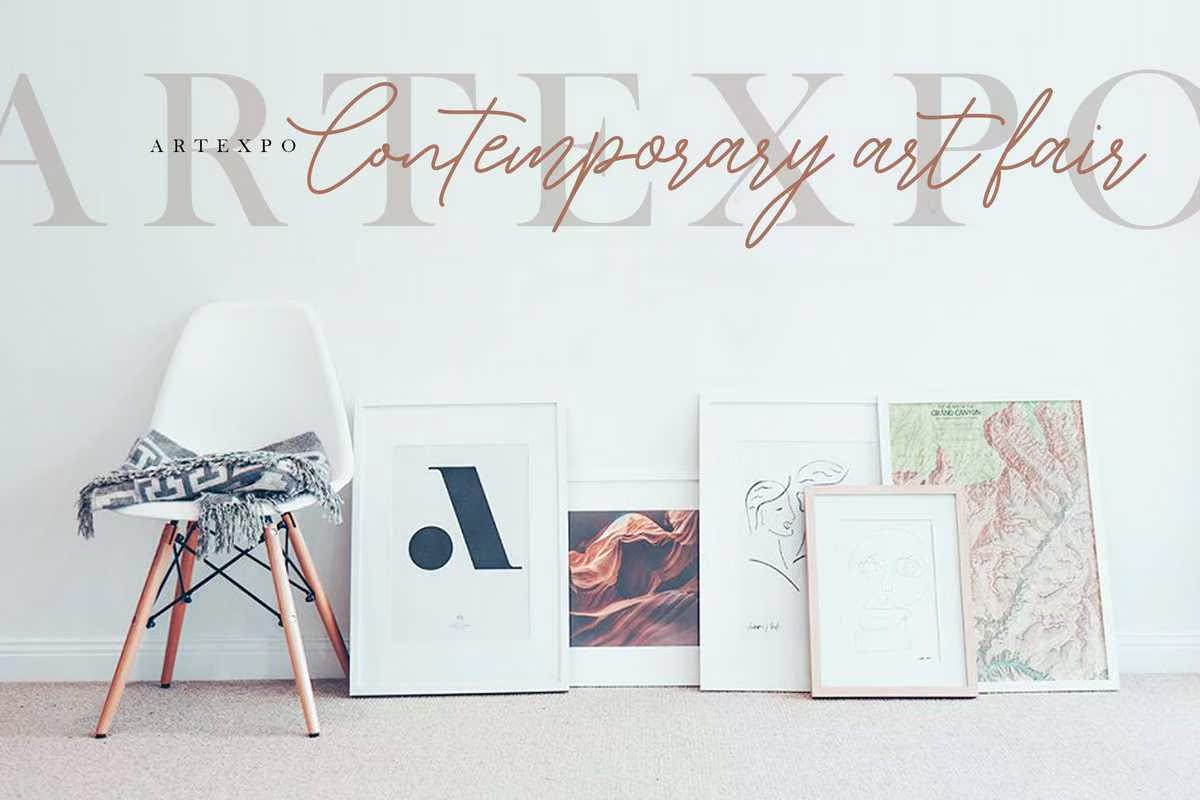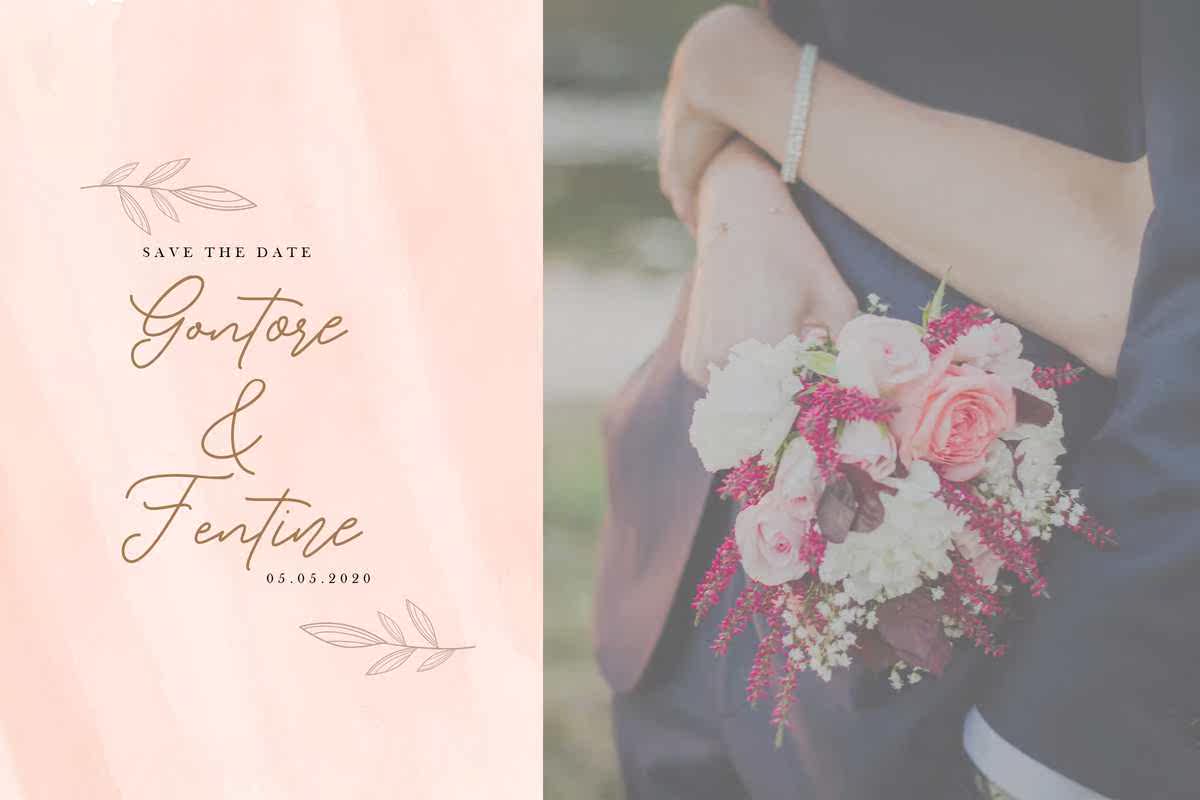
一些TimeFont是具有自然和有机外观的单一品牌。一些TimeFont是品牌项目、徽标、婚礼设计、社交媒体、广告、产品包装、产品设计、标签、摄影、水印、邀请、,文具商和需要手写品味的项目。有时是与自然和有机外观的单一元素。有时是完美的品牌项目、徽标、婚礼设计、社交媒体、广告、产品包装、产品设计、标签、照片、水印、邀请、需要手写品味的文具商和项目。